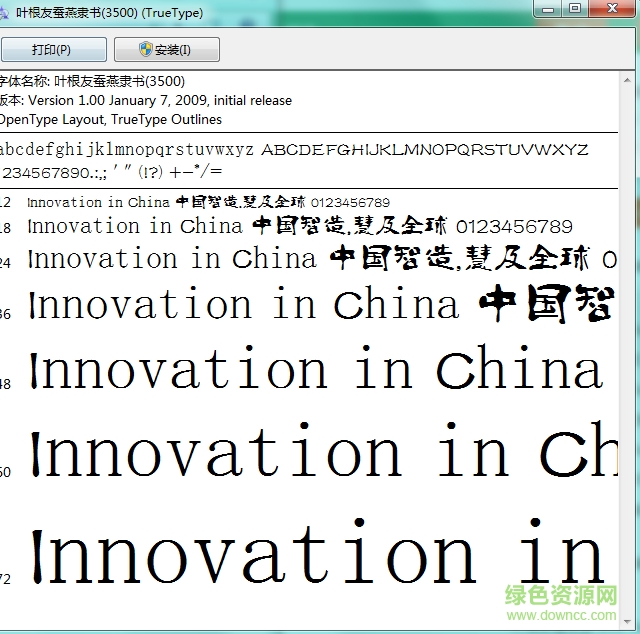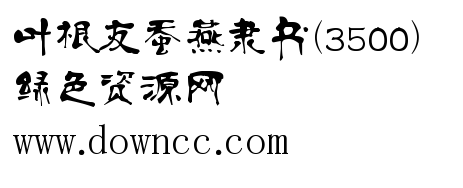
葉根友蠶燕隸書(3500)是一款測試版書法字體,通過毛筆進(jìn)行創(chuàng)作,整體娟秀不失大氣,透露著一種穩(wěn)重時尚的雜糅體驗(yàn),綠色資源網(wǎng)歡迎大家免費(fèi)下載!
親于自然,寫于生活,利用書法和對現(xiàn)代藝術(shù)的審美,設(shè)計出此款字體,遒勁有力,字體大方有內(nèi)涵,賦予了字體筆畫的一種干勁力量。